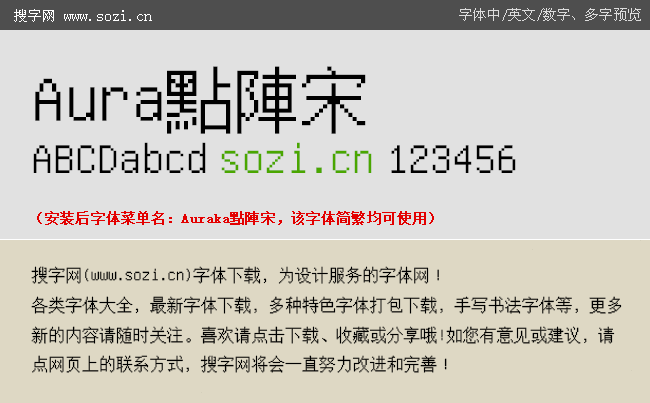
Aura點(diǎn)陣宋字體
搜字網(wǎng)提供一款A(yù)ura點(diǎn)陣宋字體中文字體下載,Aura點(diǎn)陣宋字體是一款以宋體為原形設(shè)計(jì)的中文點(diǎn)陣藝術(shù)字體,字體非常有趣,效果非常出色,適合應(yīng)用于廣告設(shè)計(jì)、名片設(shè)計(jì)、產(chǎn)品設(shè)計(jì)等個(gè)性應(yīng)用。